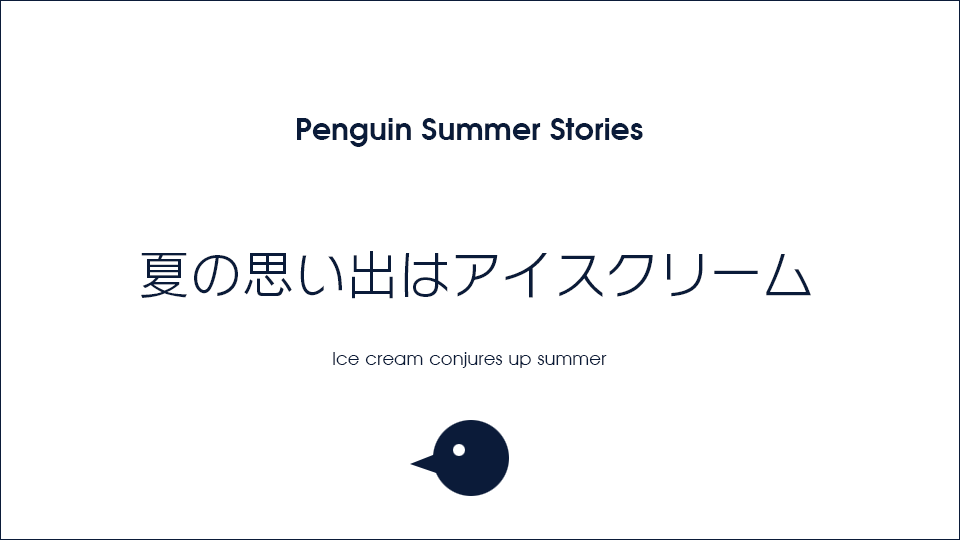
Avian フォントの作例
Avian フォントの作例です。
概要
モダンな字体の欧文フォントです。視認性も良いです。
作例
作例1
Avian フォントの作例:画像1
モダンな字体です。Boldの書体もやぼったくなく視認性も良いです。
作例2
Avian フォントの作例:画像2
日本語フォントの「ロダンNTLG」と組み合わせるとすっきりしたモダンなデザインになります。